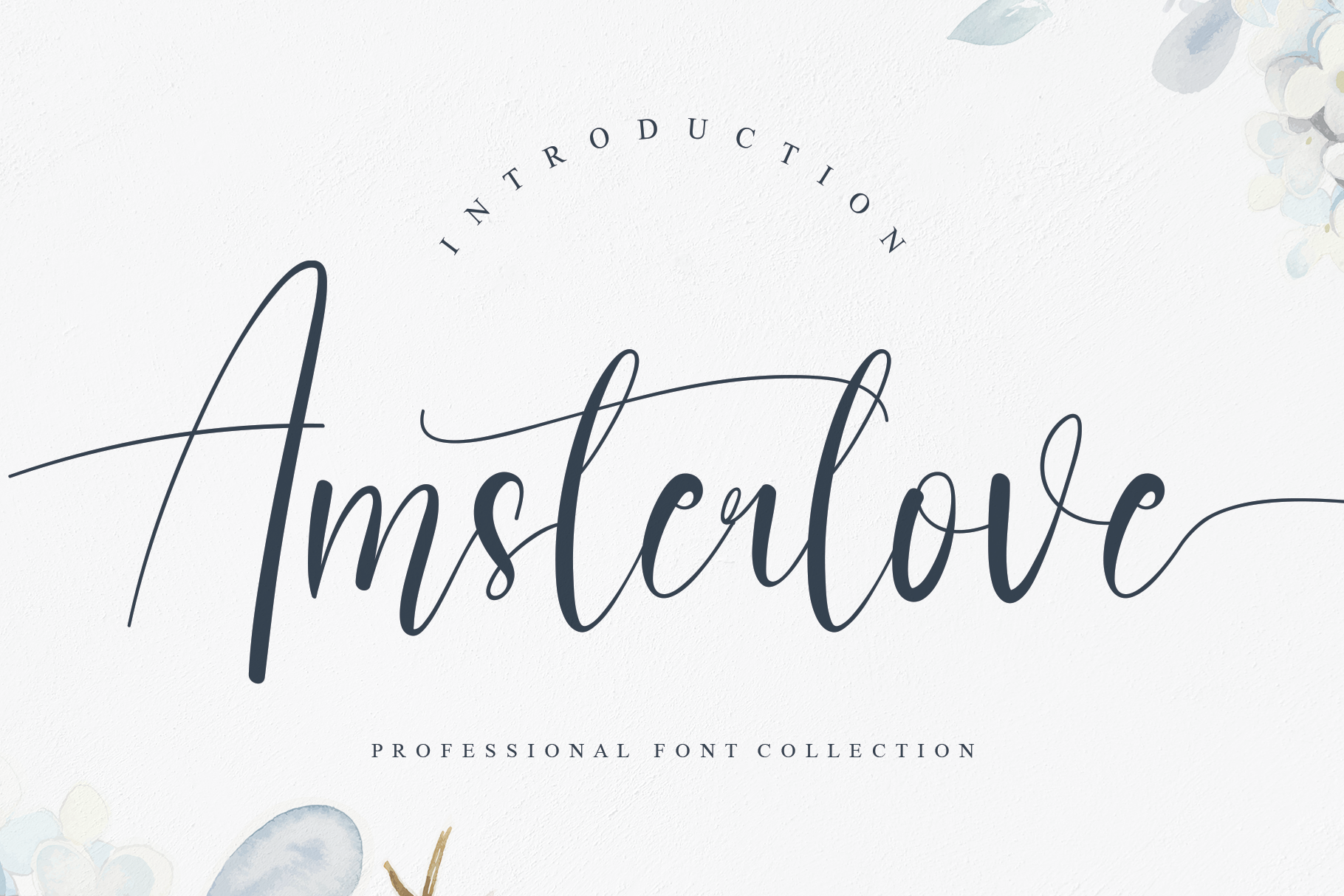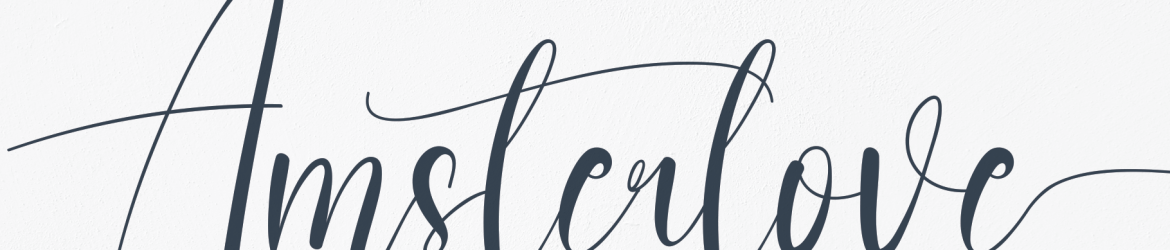
A ‘Amsterlove Font’ é uma elegante fonte escrita a mão com traços leves que carrega um toque único e impacto visual impressionante. Perfeita para aqueles projetos de design desejando adicionar um toque luxuoso, esta fonte vai transformar qualquer layout em um projeto notável. Composta por uma mistura delicada e suave da escrita a mão, combinada com traços finos e sutis, ela traz consigo o charme sofisticado de uma elegante cartilha, mas mantendo uma presença que se adapta perfeitamente para aplicações modernas. Ideal tanto para nomes de marca quanto para mensagens pessoais, a ‘Amsterlove Font’ oferece uma solução multifuncional que pode ser usada em qualquer projeto criativo.